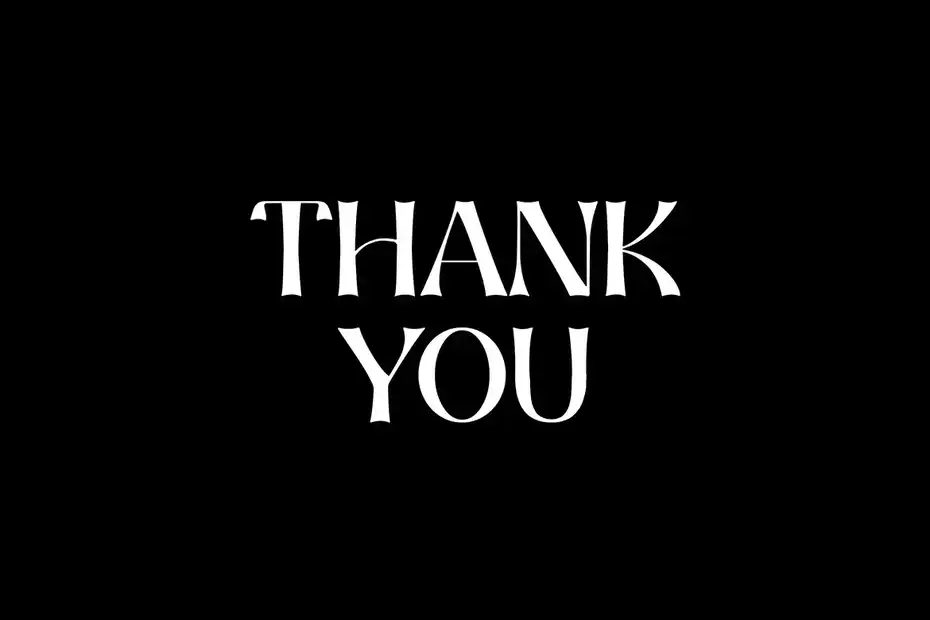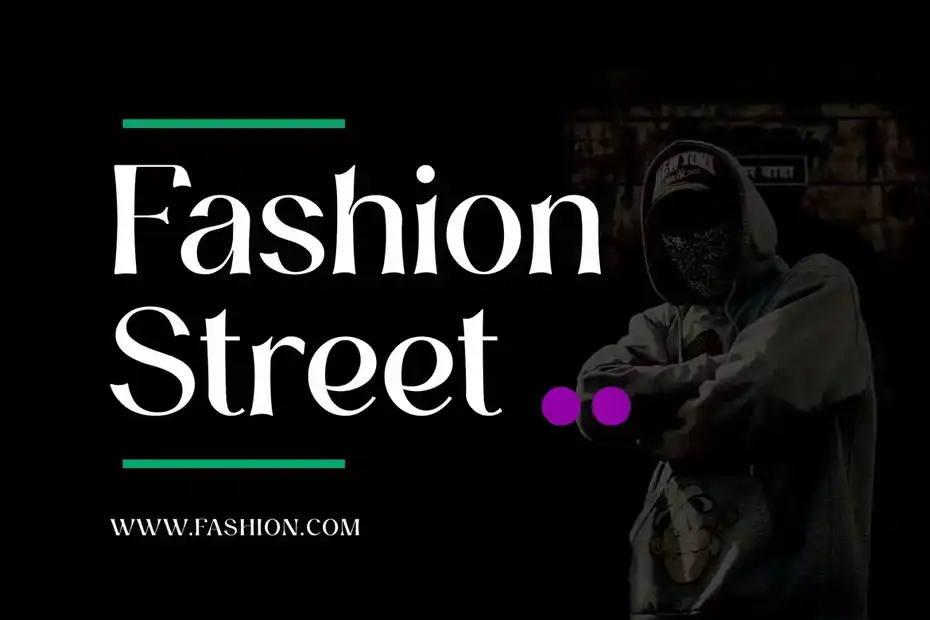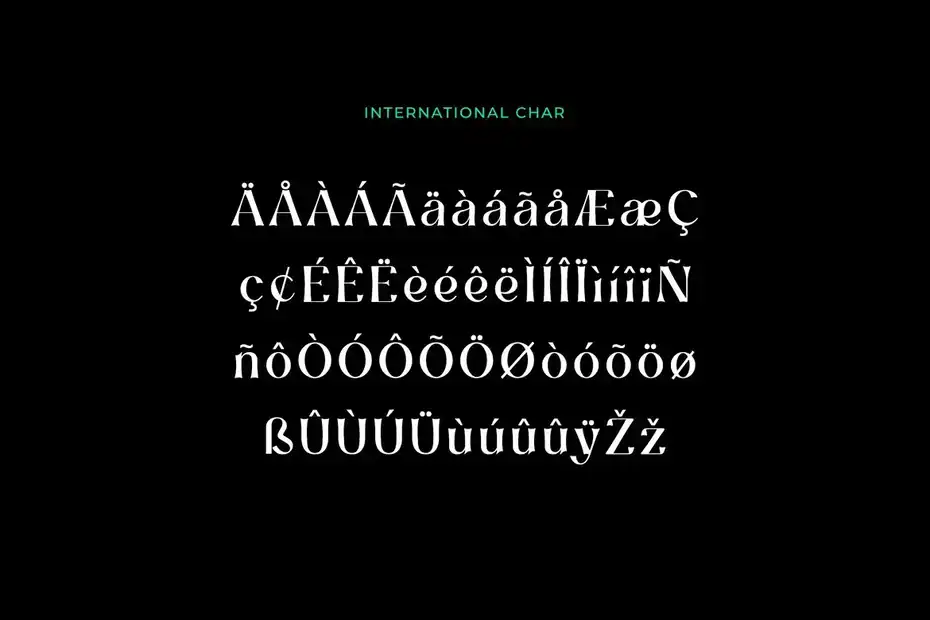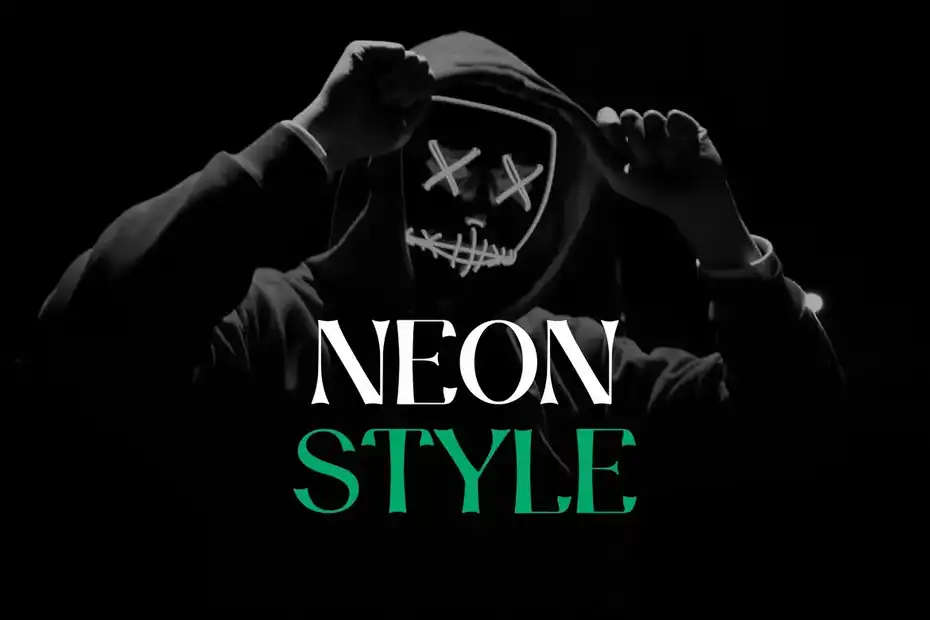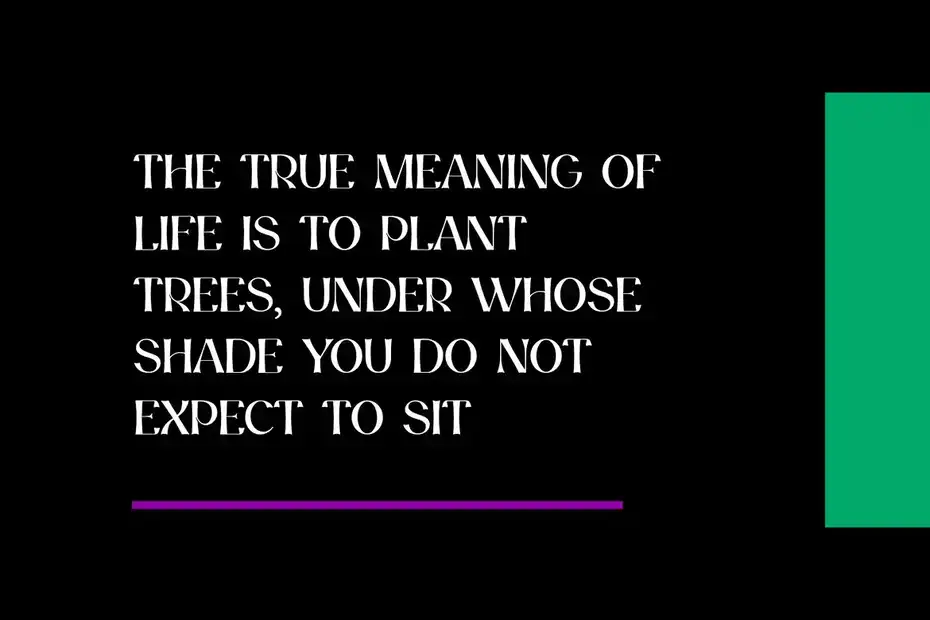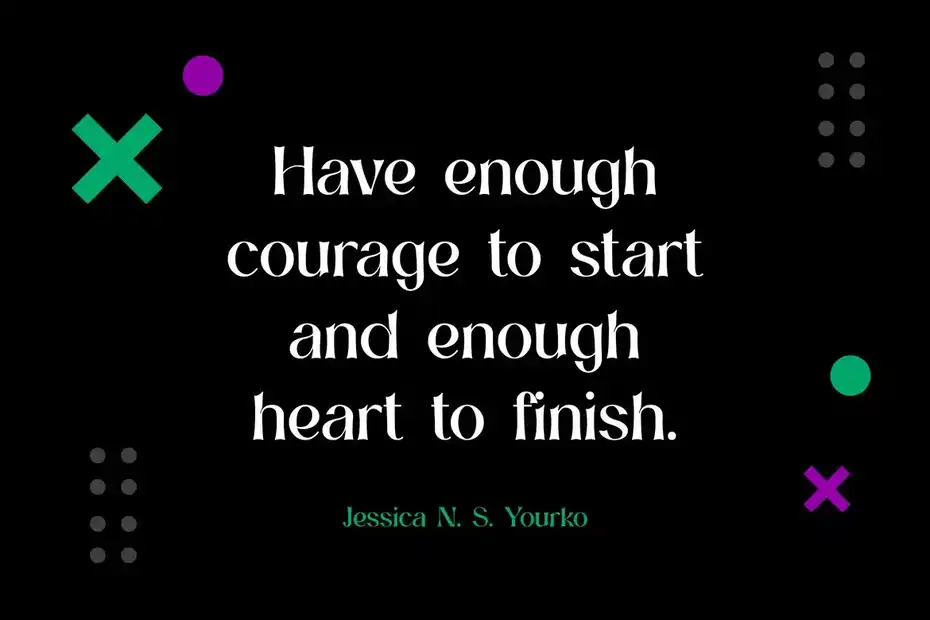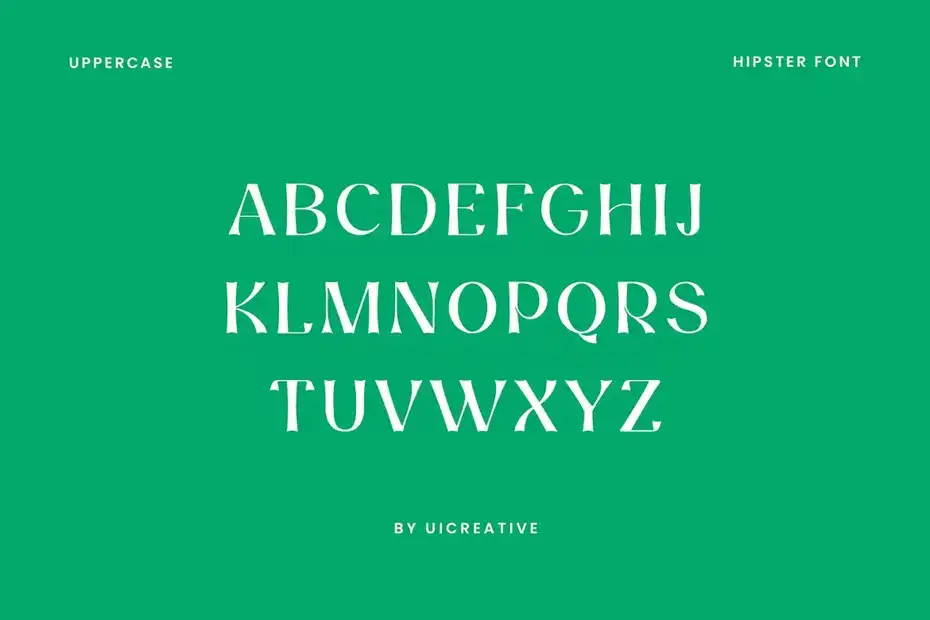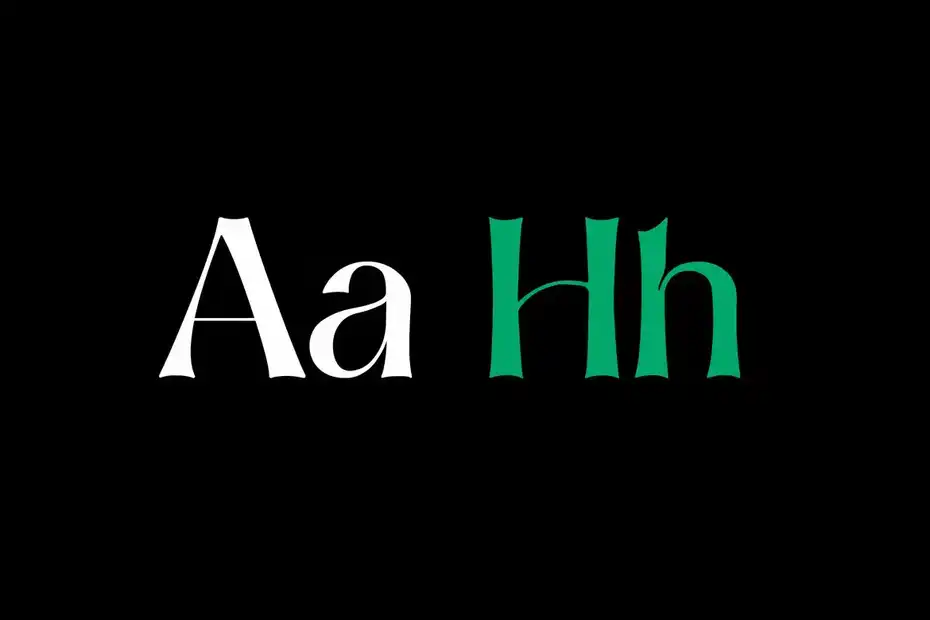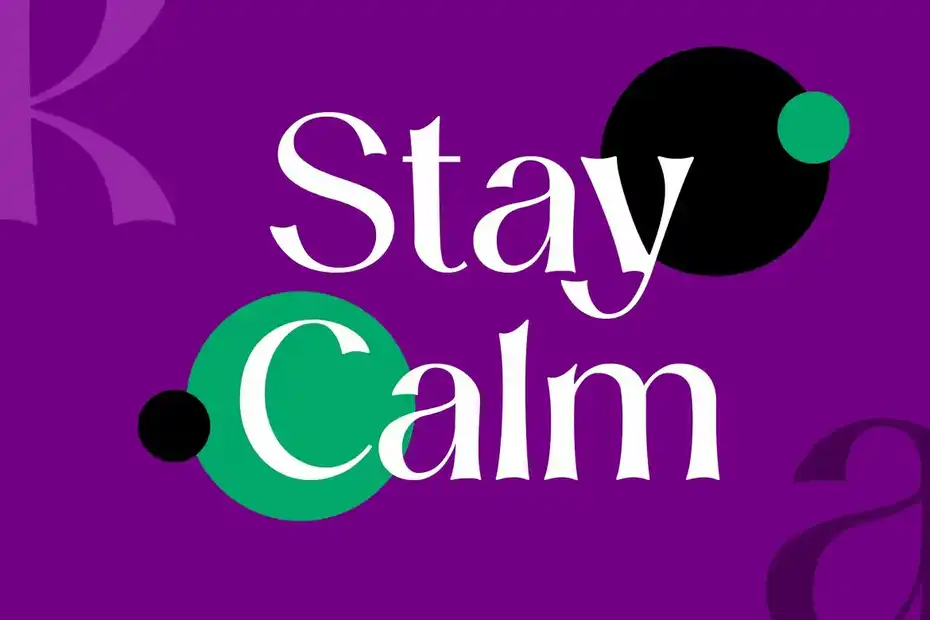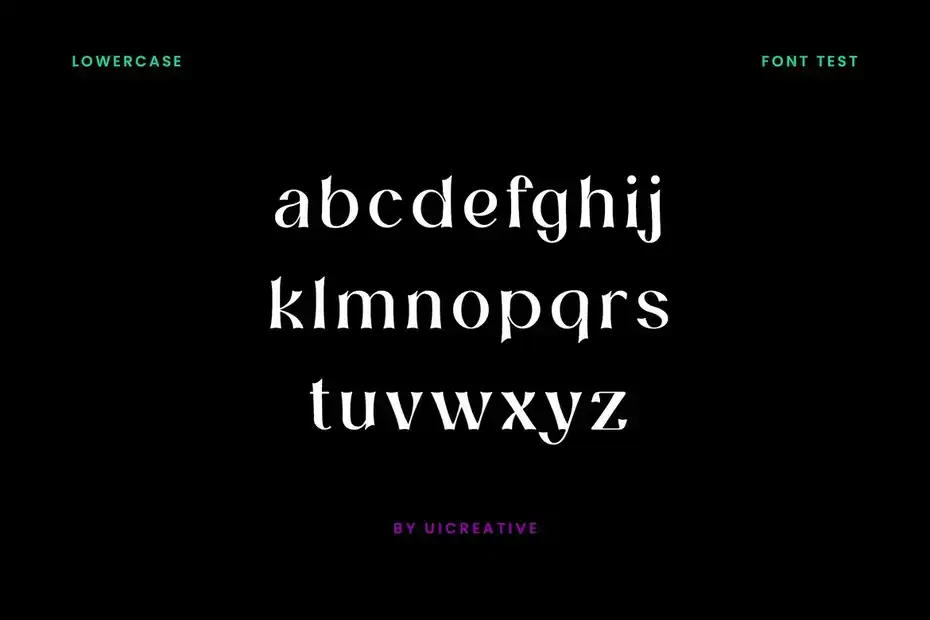
دانلود فونت لاتین Milkway Hipster Sans Serif Font
دانلود فونت لاتین Milkway Hipster Sans Serif Font : این فونت یک فونت انگلیسی مدرن Sans Serif لاتین است که برای پروژه های مختلف مانند: امضا، برندینگ، لوگو، عروسی، نقل قول تایپوگرافی، جلد مجلات یا کتاب، سربرگ وب سایت، لباس، طراحی بسته بندی و غیره مناسب میباشد.
• سبک: Sans-Serif